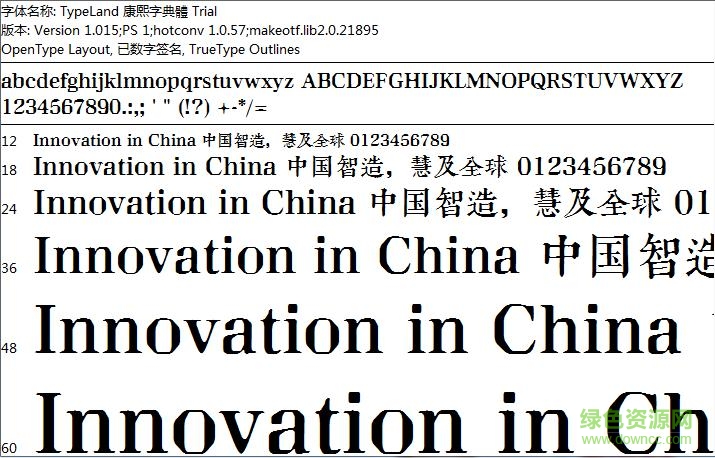
文悅康熙字典體是文悅字庫中一款非常受歡迎的中文字體,在國外非常的受歡迎,這款字體與大家熟悉的宋體字體類似,但是具有強(qiáng)烈的個性,喜歡的朋友歡迎下載使用!
文悅康熙字典體是一款根據(jù)經(jīng)典名著康熙字典中的字體研發(fā)而來,是一種古代的印刷字體,具有非常鮮明的書法風(fēng)格以及時代的特征,非常適合用來進(jìn)行創(chuàng)作!